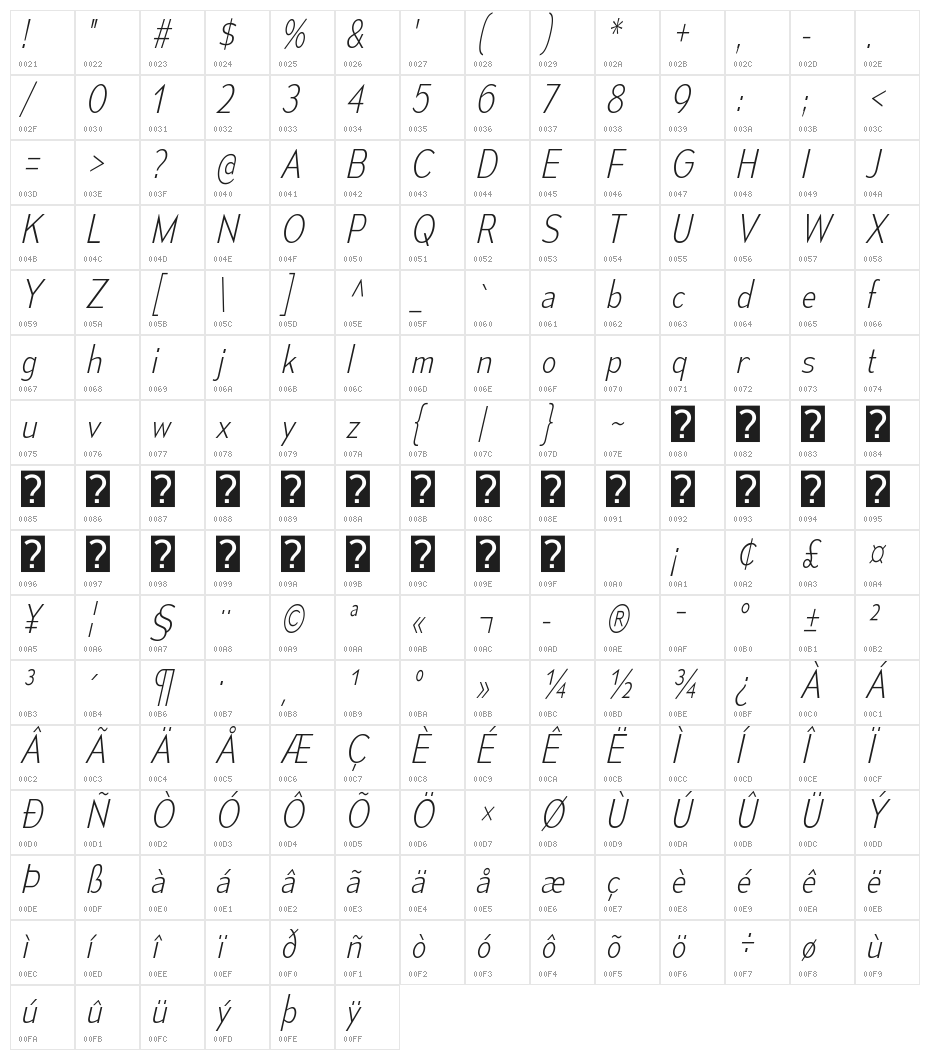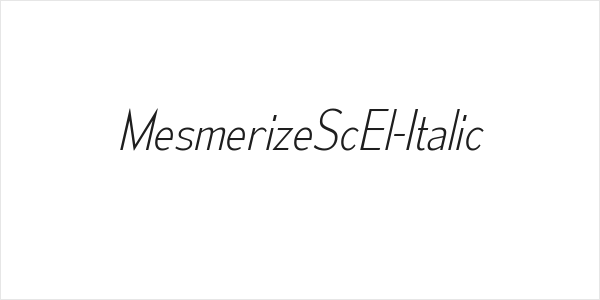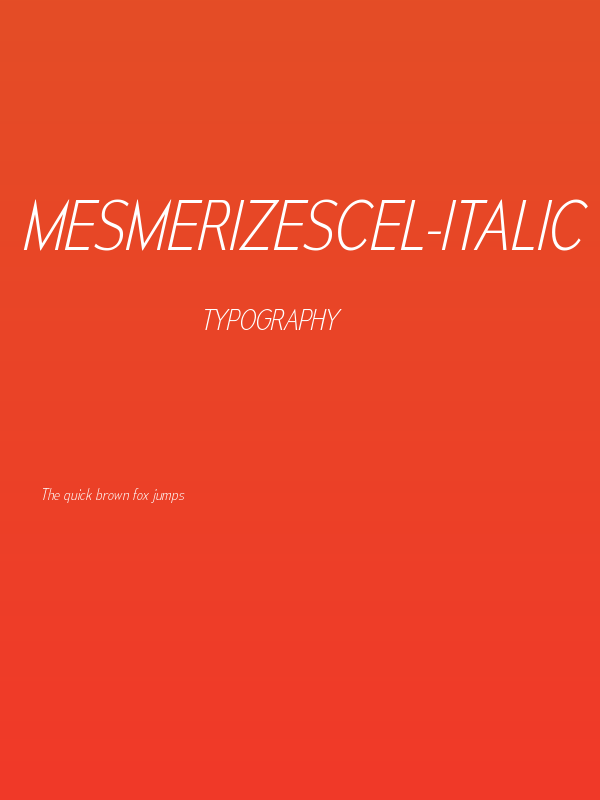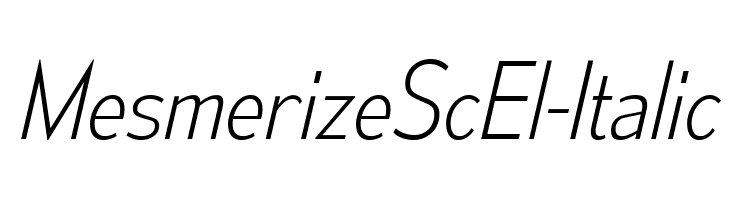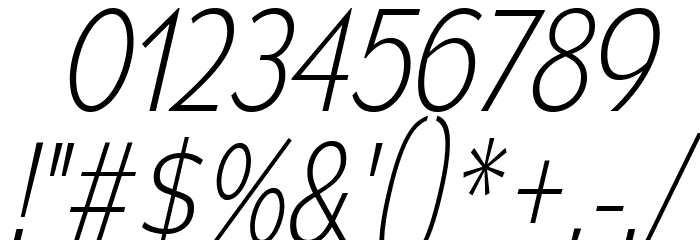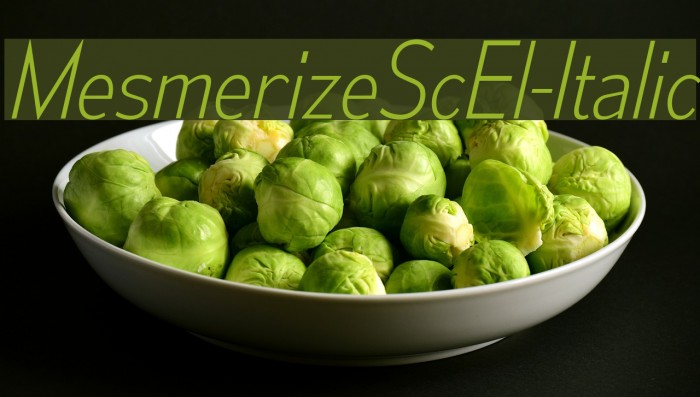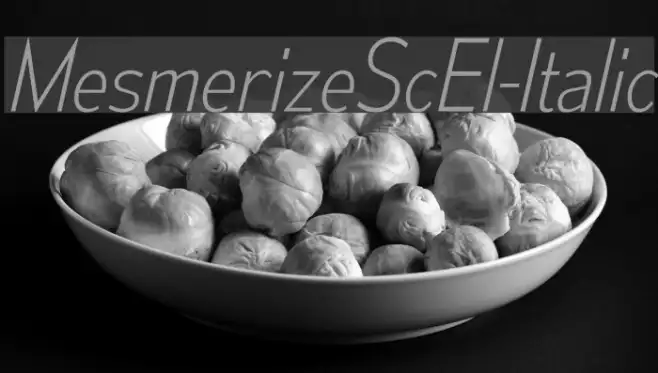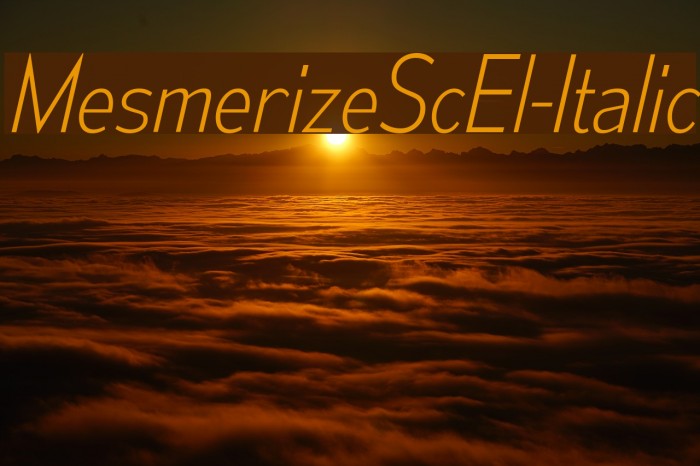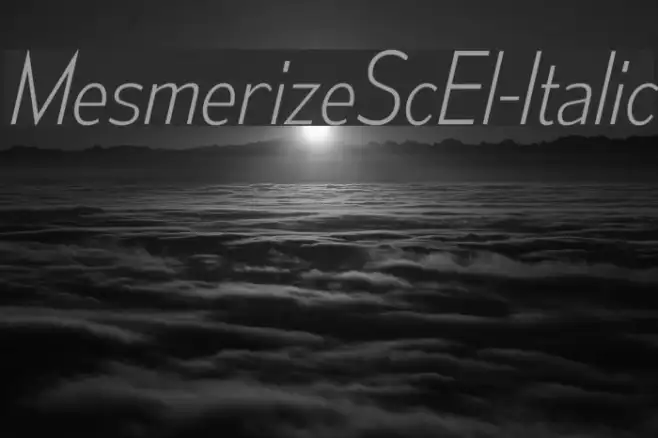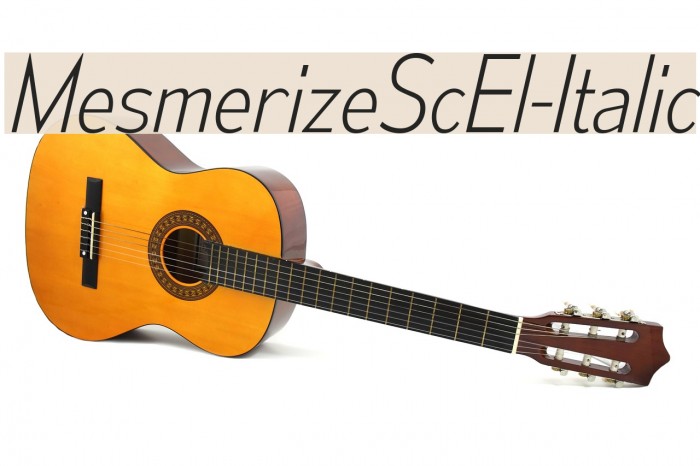
MesmerizeScEl-Italic Font
| Anwendungsfall | Headlines, Body text, Logos |
| Vorgeschlagene Projekte | Ideal for branding, editorial design, advertising, and digital interfaces where a modern and stylish look is desired. |